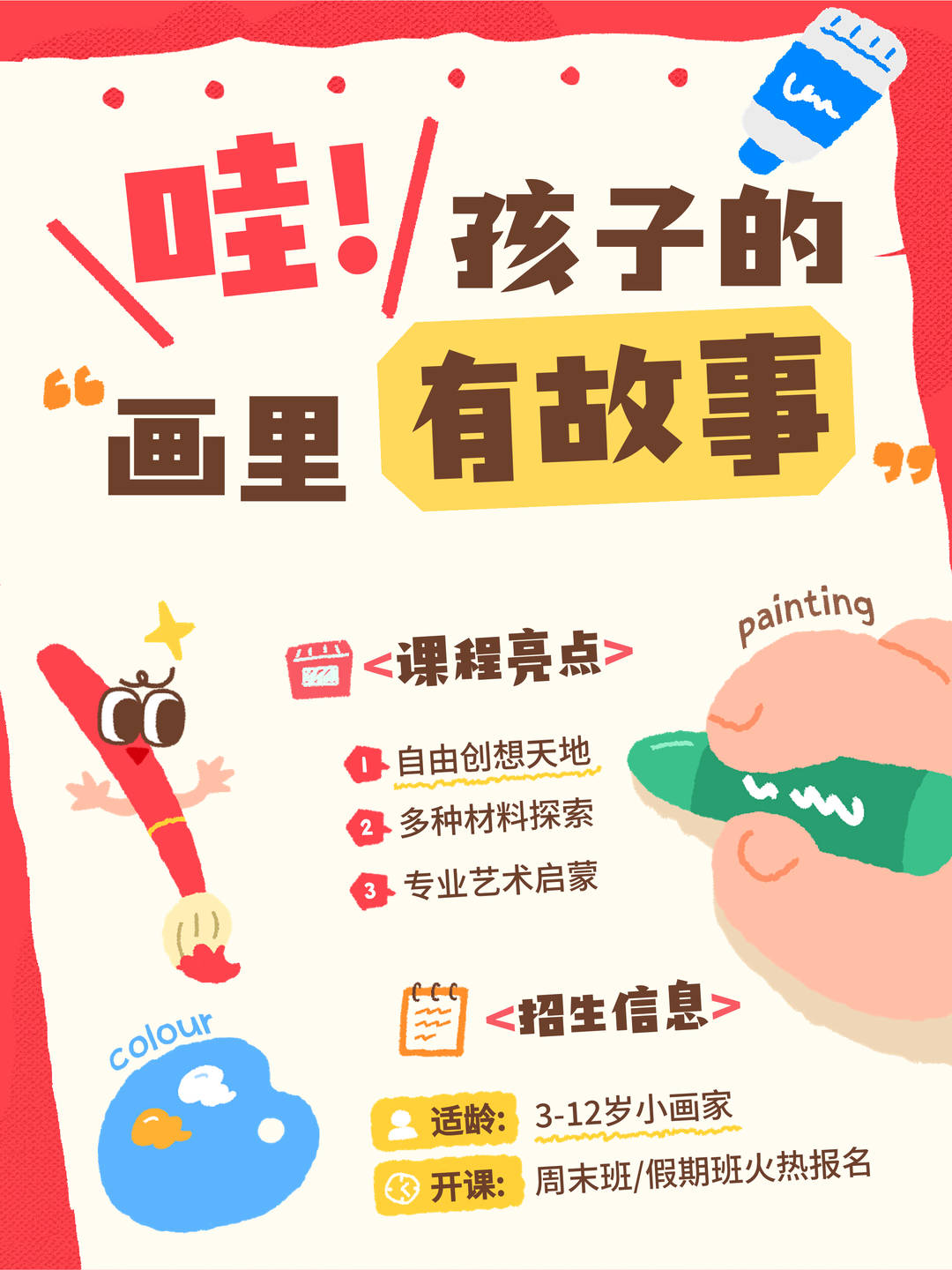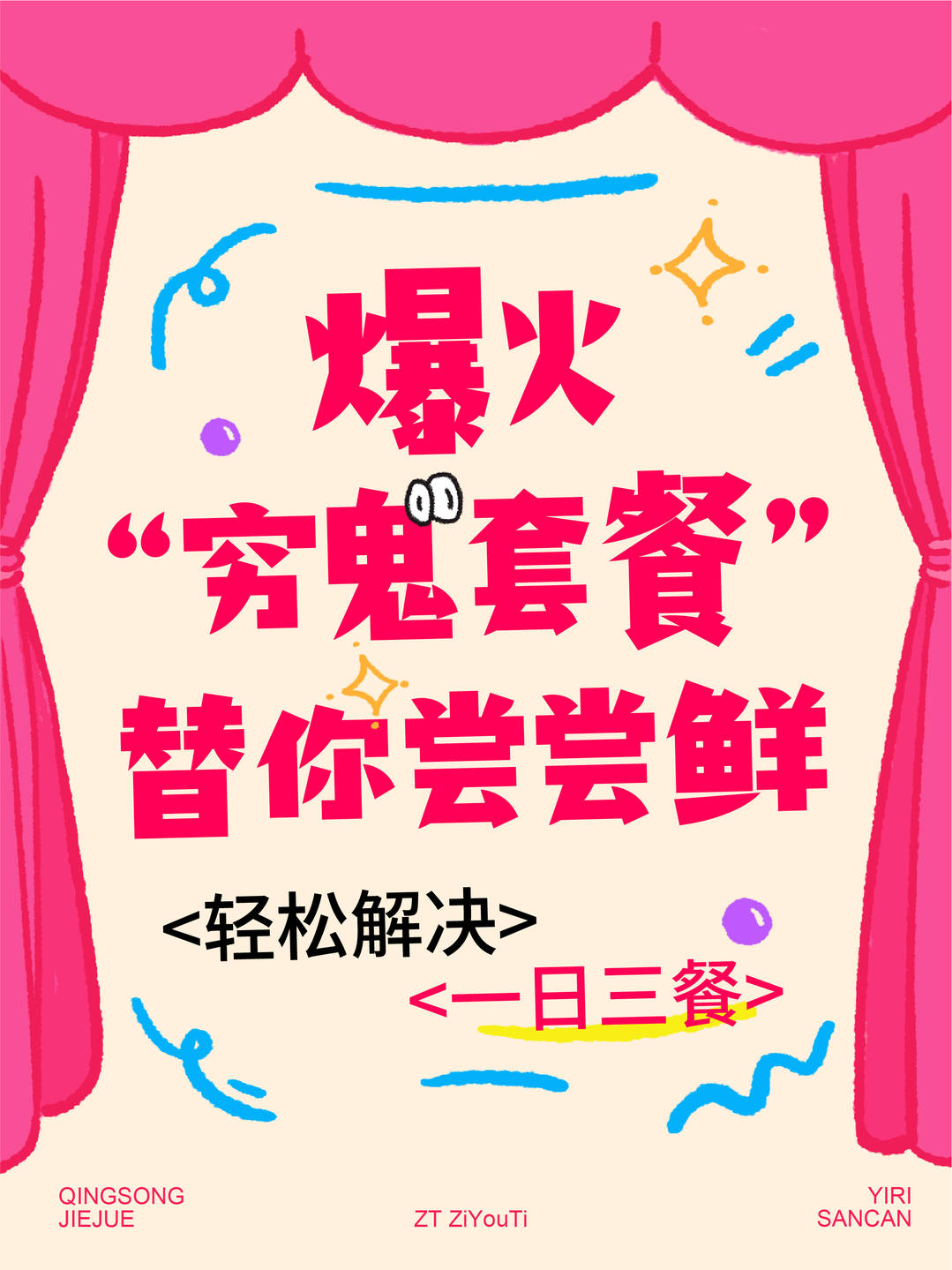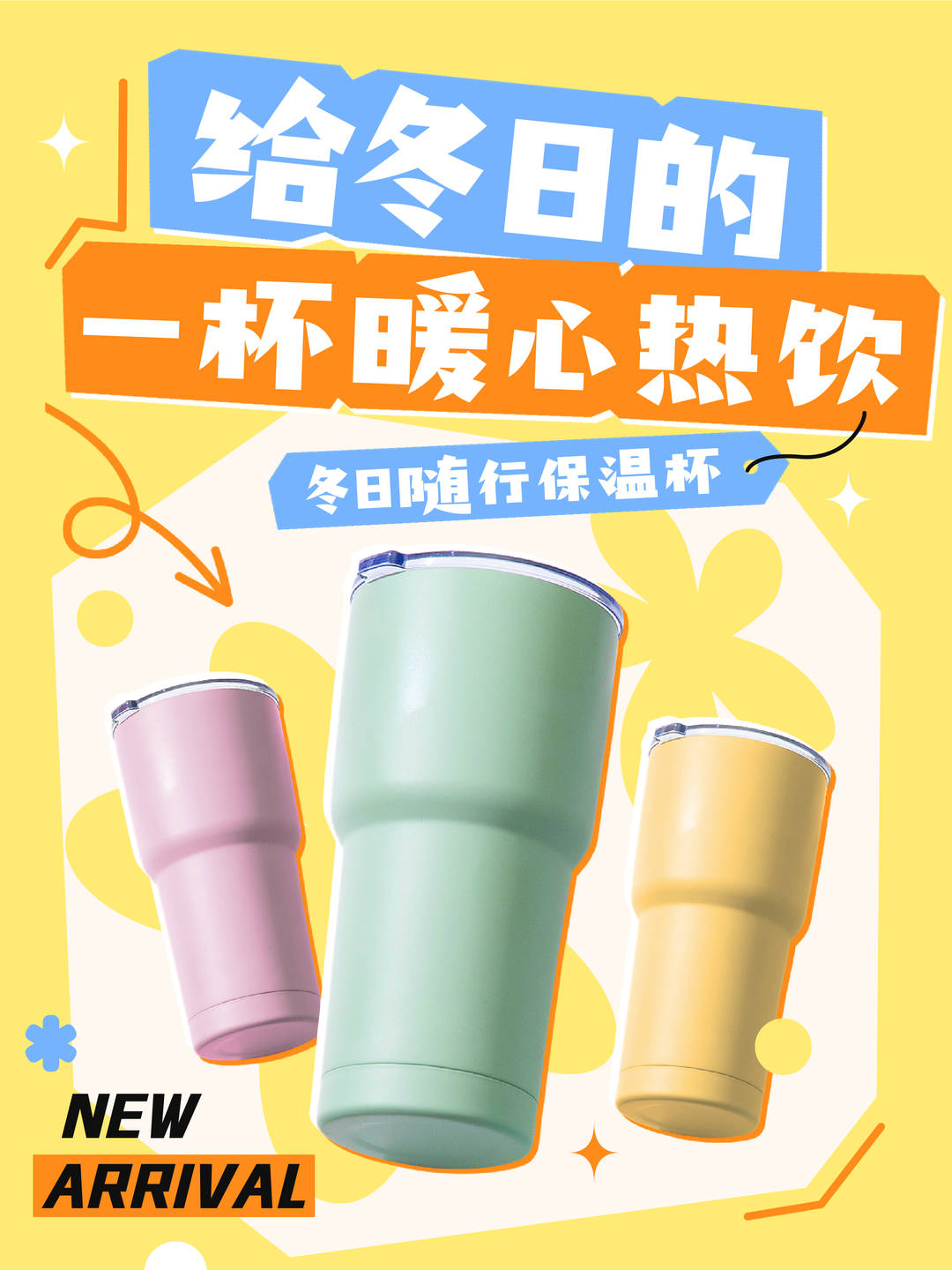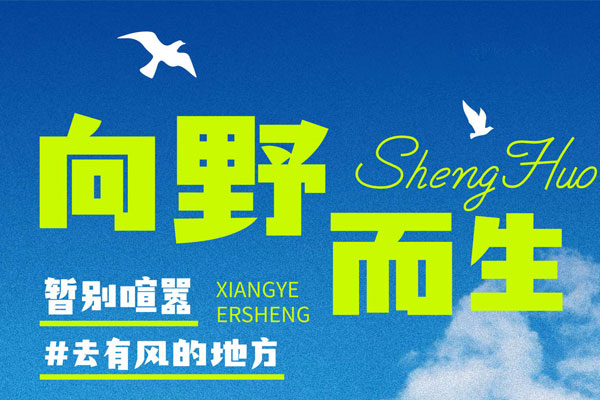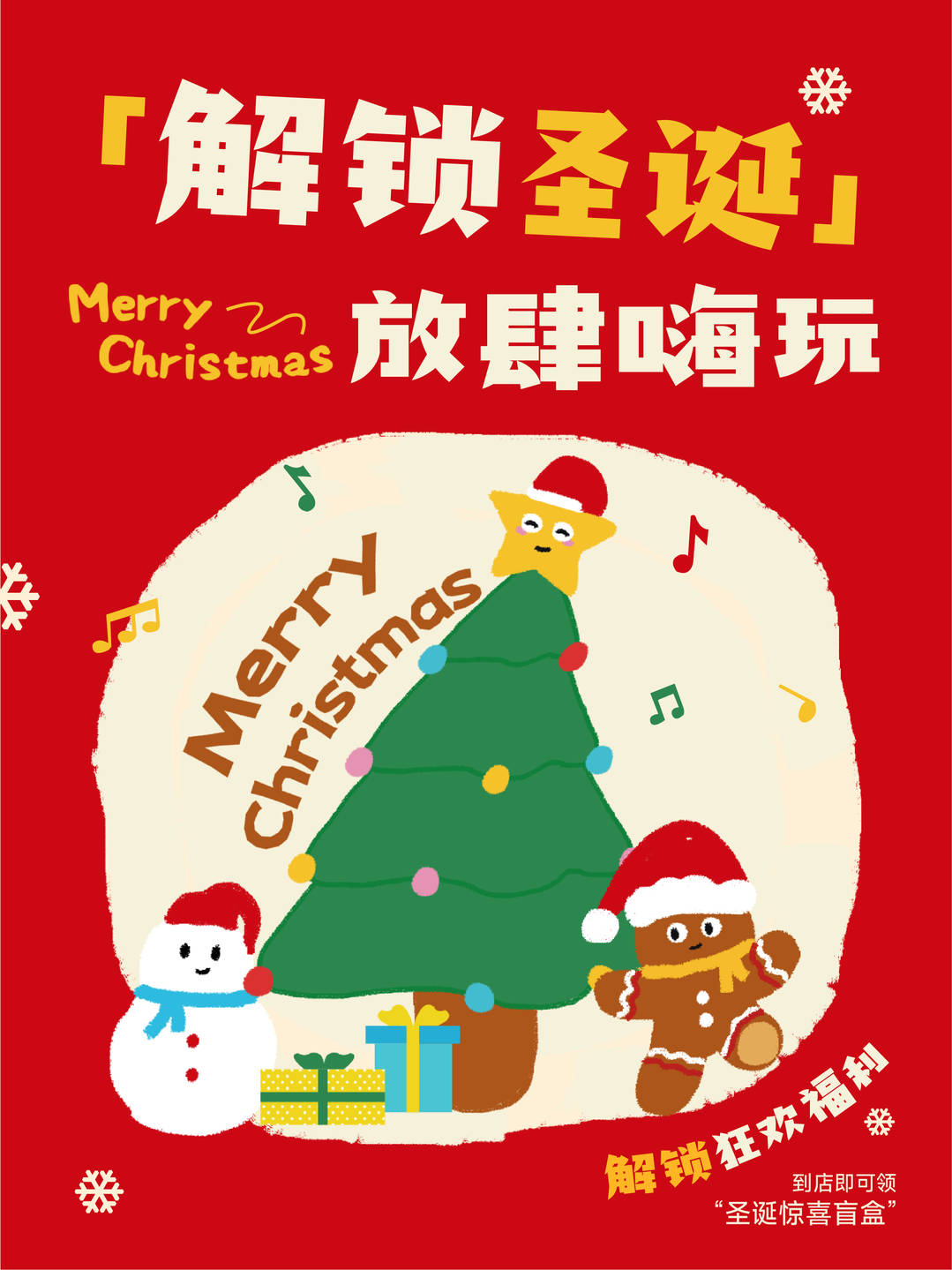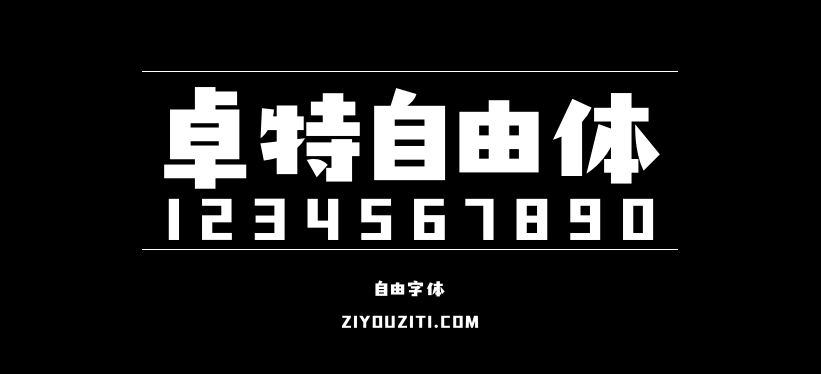
卓特自由体
卓特自由体字形结构宽阔,大小错落,节奏感强烈。笔画粗实有力,几何感强,整体风格张扬惊艳,极具视觉冲击力。经自由字体检测,目前卓特自由体已覆盖GB2312规范的6763字,日常使用不会遇到缺字情况。
卓特自由体是一款由卓特视觉发布的开源简体中文字体,依据 SIL Open Font License 1.1(OFL)协议免费向公众开放使用。
本字体包含 GB2312-80 标准中的 6763 个简体汉字及 420 个常用字符,共收录 7183 个字符,可满足日常办公、设计创作、品牌宣传等多元场景的字体使用需求。